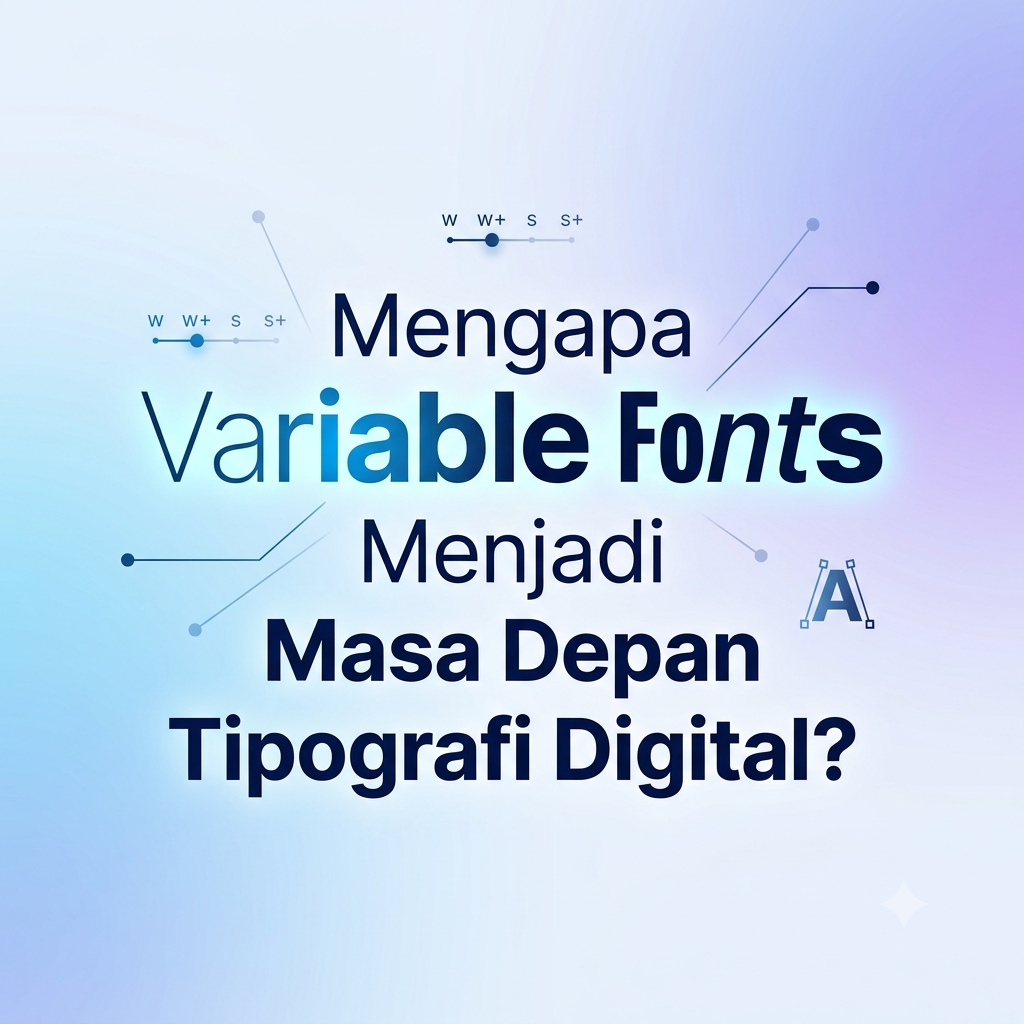
Mengapa Variable Fonts Menjadi Masa Depan Tipografi Digital?
1. Apa Sih Variable Fonts Itu? (Satu File buat Semua Gaya!)
Biar gampang dibayangin, font tradisional itu ibarat foto biasa yang ukurannya udah terkunci. Kalau lo mau ukuran atau ketebalan beda, lo harus punya file foto yang lain.
Nah, Variable Fonts itu ibarat slider di aplikasi edit foto. Cuma dengan satu file font tunggal, lo bisa ngatur ketebalan (weight), kemiringan (slant), lebar huruf (width), hingga gaya dekoratif lainnya secara dinamis dan fleksibel!
Gampangnya: Daripada lo download 18 file terpisah untuk satu font family, lo cuma butuh 1 file Variable Font yang sudah mencakup semua variasi gaya tersebut. Praktis banget, kan?
2. Alasan Utama Variable Fonts Jadi Masa Depan Tipografi Digital
A. Bikin Website Anti-Lemot (Ultra-Fast Loading)
Ukuran file itu musuh utamanya kecepatan website. Kalau lo pakai banyak variasi font biasa, browser harus mengunduh belasan file sekaligus yang bikin situs jadi berat.
Dengan Variable Fonts, ukuran filenya jauh lebih kecil secara akumulatif. Website lo bakal loading kilat, dan ini disukai banget sama algoritma Google buat ningkatin peringkat SEO!
B. Desain Lebih Fleksibel & Responsive
Pernah gak lo ngelihat teks di layar HP kelihatan terlalu gemuk atau bikin tampilan pecah, tapi pas dibuka di laptop kelihatan pas?
Dengan Variable Fonts, lo bisa ngatur ketebalan dan lebar huruf secara otomatis sesuai dengan ukuran layar pengguna (Responsive Typography). Jadi, visual teks lo bakal selalu kelihatan estetik dan enak dibaca di perangkat mana pun!
C. Efek Animasi & Interaksi yang “Slay”
Ini dia fitur yang paling disukai Gen Z! Karena sifatnya yang dinamis, Variable Fonts bisa dianimasikan pakai CSS atau JavaScript dengan halus banget.
• Tulisan bisa menebal secara otomatis pas kursor hover di atas teks.
• Font bisa berubah bentuk mengikuti gerakan scroll atau irama audio.
• Bikin tampilan UI/UX website lo kelihatan interaktif dan futuristik!
3. Komparasi: Font Tradisional vs Variable Fonts
Biar makin jelas bedanya, coba intip perbandingannya di tabel ini:
Fitur / Karakteristik Font Tradisional Variable Fonts
Jumlah File Banyak (1 file untuk 1 gaya) Cukup 1 file untuk semua gaya
Ukuran Total File Berat / Besar Ringan & Efisien
Kebebasan Variasi Terbatas pada preset (Bold, Light, dll) Tanpa batas (bisa digeser pakai slider)
Interaktivitas & Animasi Kaku / Terbatas Super halus & dinamis
Responsivitas Layar Cenderung statis Sangat fleksibel mengikuti layar